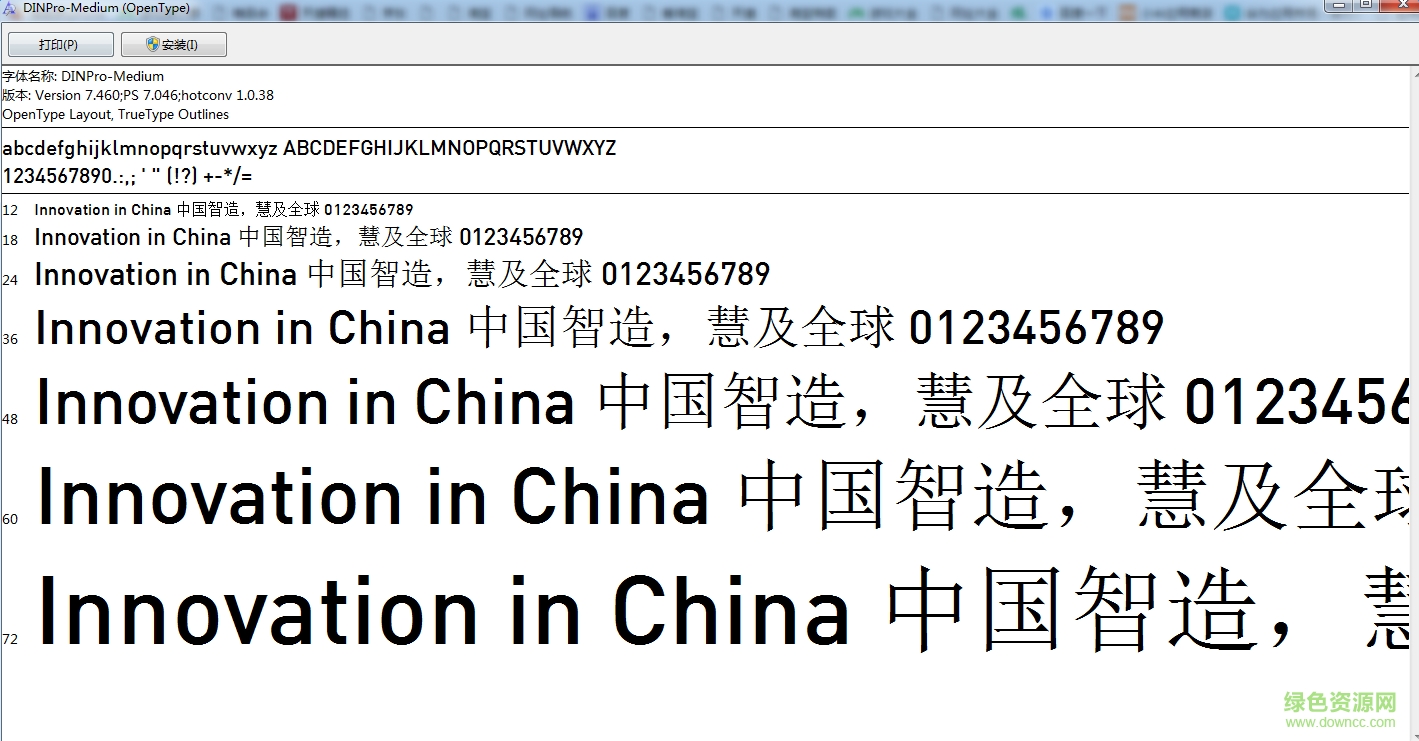
dinpro medium字體是一款中等大小的英文字體,該字體字型規(guī)整、線(xiàn)條流暢,簡(jiǎn)潔干凈毫無(wú)多余裝飾,可應(yīng)用于書(shū)刊、雜志、宣傳海報(bào)等領(lǐng)域,歡迎大家在綠色資源網(wǎng)下載!
英文字體分為兩大類(lèi),serif以及sans serif。
serif,意思是在字的筆畫(huà)開(kāi)始、結(jié)束的地方有額外的裝飾,而且筆畫(huà)的粗細(xì)會(huì)有所不同。
sans serif,是無(wú)襯線(xiàn)字體,沒(méi)有這些額外的裝飾,而且筆畫(huà)的粗細(xì)差不多。